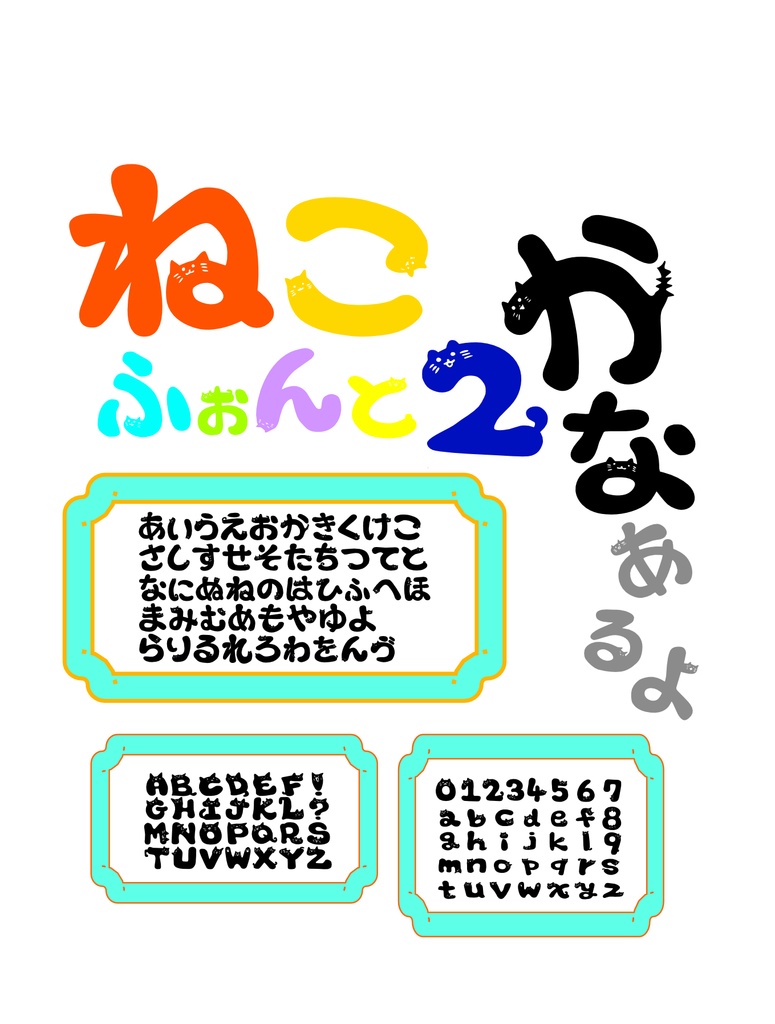
rakugakimacky11ネコフォント【かな追加ver】Digital300 JPYAdd to CartBuy a GiftAbout Giftネコフォントにひらがなが追加されたバージョンです。 商用利用ご自由にどうぞ お気に入りはやんのかステップしている「か」です カーニングや文字幅などはネコなので適当です ご了承くださいrakugakimacky11Visit FANBOX!FontsNekoフォントrakugakimacky110 JPY